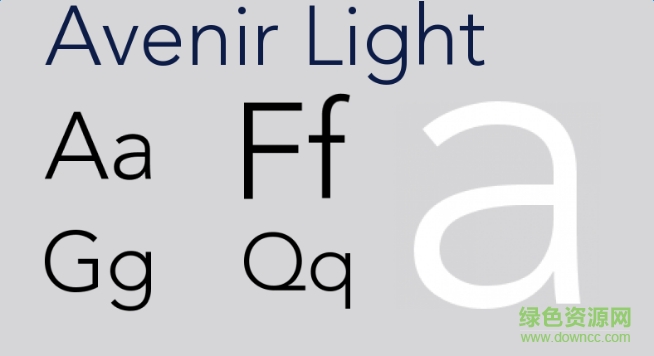
avenir light是什么字體?avenir light是廣泛應(yīng)用于各大商業(yè)領(lǐng)域的英文字體,字體線條干凈,變化自然,毫無多余點(diǎn)綴,需要的朋友歡迎在綠色資源網(wǎng)下載!
avenir被視為現(xiàn)代主義在字體設(shè)計(jì)界的典型代表,是一款經(jīng)典的無襯線字體,剝除了多余的細(xì)節(jié),以標(biāo)準(zhǔn)的幾何形體做結(jié)構(gòu)。反而是這種沒有任何風(fēng)格的字體形式成為了一種風(fēng)格。越簡約,越現(xiàn)代,因此常用于現(xiàn)代企業(yè)的logo設(shè)計(jì)、雜志排版、導(dǎo)視系統(tǒng)等!